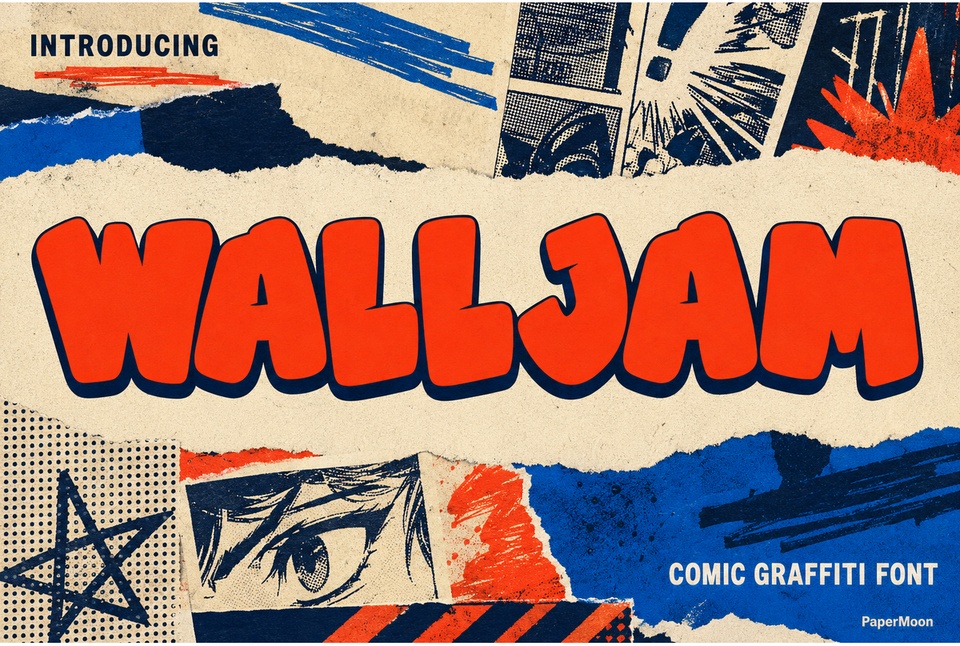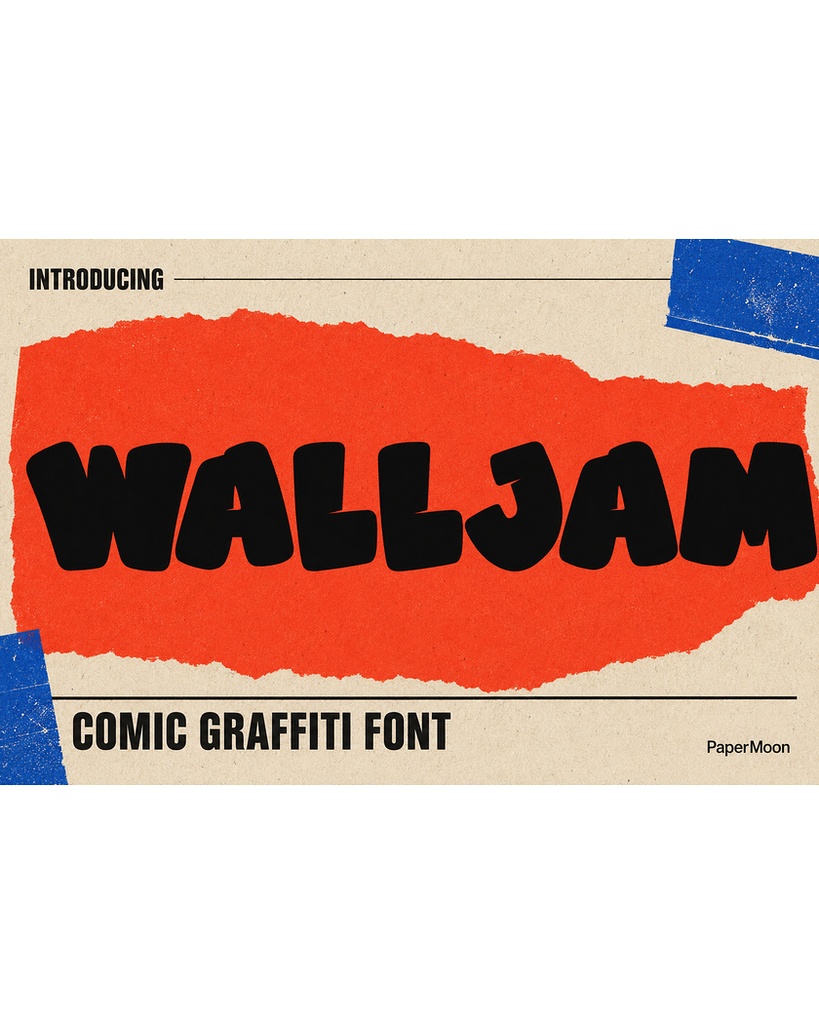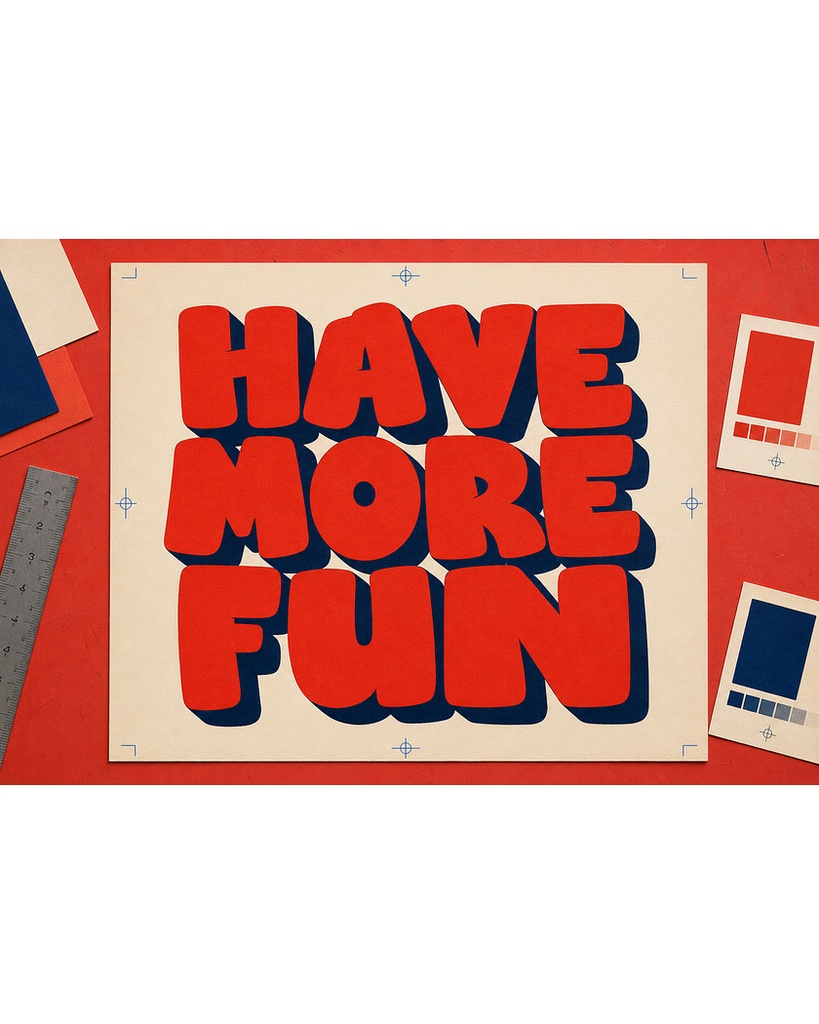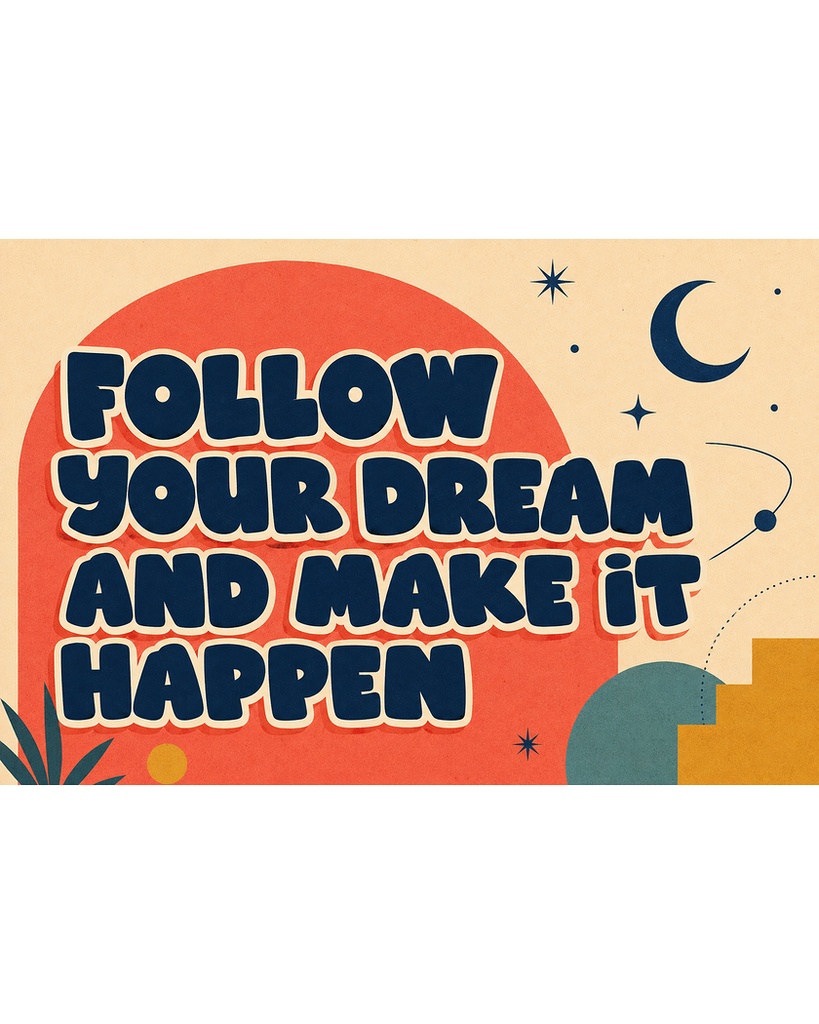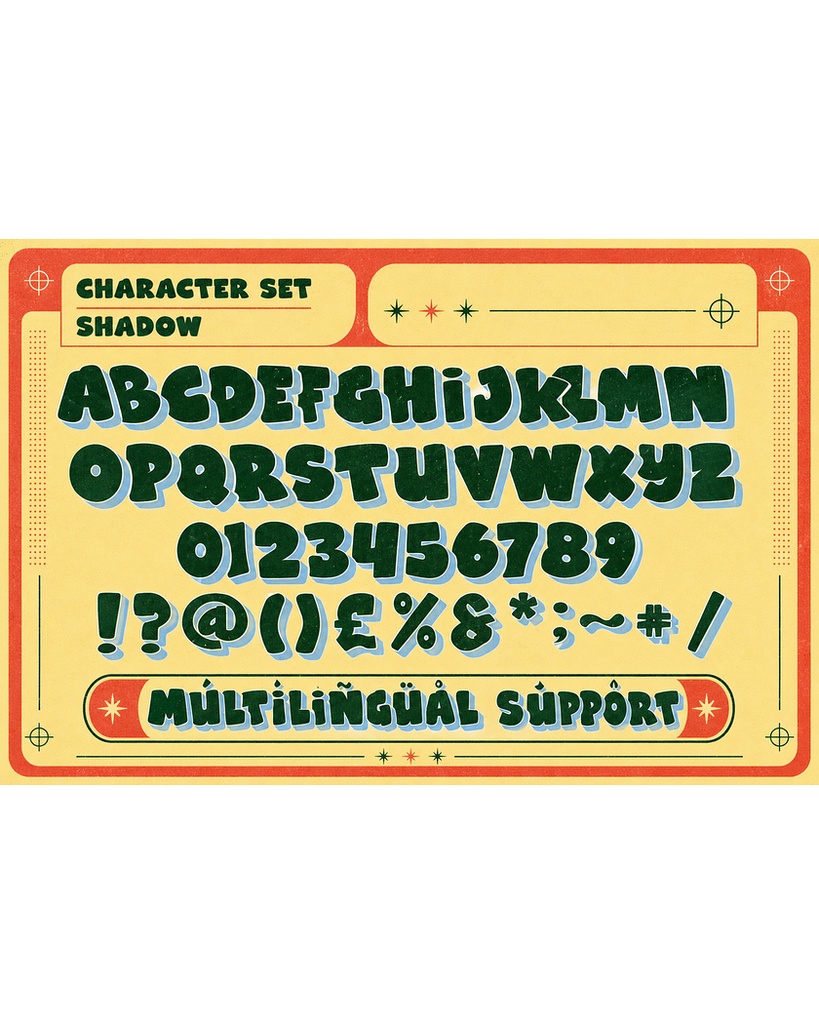
WallJam - 3Dシャドウ内蔵のコミック風グラフィティディスプレイフォントデュオ
**WallJam**は、目を引く手描き文字を求めるデザイナーのために作られた、コミック×グラフィティスタイルのディスプレイフォントデュオです。太く存在感のある大文字、弾むようなリズム、マーカーで描いたようなエネルギーが、見出しに本格的なストリートアートフォントの雰囲気を与えます。一方で、遊び心のあるコミックブックらしいテイストが、攻撃的になりすぎず親しみやすい印象を演出します。ストリートアート系のディスプレイフォントとして、WallJamはポスターやバナーなどの大きなサイズで特にその魅力を発揮し、不規則な手描きペイントの質感を存分に楽しめます。 ### WallJamとは WallJamは、異なる2つのスタイルを組み合わせて使える、本格的なフォントデュオです。**WallJam Regular**は、力強い字形と不規則な手描きテクスチャを備えた、コミックブックスタイルのベースフォントです。機械的ではなく、手作業で描かれたような自然な雰囲気を見出しに与えます。 **WallJam Shadow**は、Regularと同じレタリングに立体的な3Dドロップシャドウを組み込んだスタイルです。この3Dシャドウフォントを使えば、追加のエフェクトレイヤーを作成することなく、1回の設定で文字に奥行きを加えられます。 ShadowスタイルをRegularの上に重ねれば、本格的な立体感のあるポスターデザインを作成できます。また、Shadowだけを使用すれば、複雑な設定なしでポップな立体感を表現できます。すべてのアウトラインは手作業で描かれ、統一感のある本格的なアーバングラフィティフォントの雰囲気になるよう丁寧に調整されています。 ### 主な特徴 各スタイルには**236種類のグリフ**が収録されており、Basic Latin、Latin-1 Supplement、西ヨーロッパ言語の句読点に対応しています。さらに、一般的な数学記号、通貨記号、numero記号、商標記号なども含まれています。 OpenTypeのGSUB機能による標準的な**fi / fl リガチャ**を搭載し、GPOSカーニングによって、どのサイズでも文字間隔をバランスよく保てます。 インストール可能な埋め込み形式を採用しているため、MacとPCの両方にスムーズにインストールできます。 WallJamは、細部まで手描きにこだわったフォントです。このような手描きディスプレイフォントは、大型ポスターから小さなラベルまで、どのサイズでも個性的な表情を保ちます。また、太く存在感のあるレタリングでありながら、限られたスペースでも読みやすさを維持します。 ### 使用用途 コミックグラフィティフォントや遊び心のあるディスプレイフォントとして、WallJamは幅広いデザインプロジェクトに活用できます。 イベントフライヤーやアルバムアートでは、インパクトのある**ポスターフォント**として活躍します。ダイカットステッカーやバッジには、個性的な**ステッカーフォント**として使用できます。 ストリートウェアのデザインでは、アパレルやグッズに瞬時に個性を与え、小規模ブランドのブランディングにも適した**ストリートウェアフォント**です。 また、パーティー招待状や学校・教室での制作物などには、親しみやすい**キッズフォント**としても使用できます。 コミックブックのレタリングをベースとしたデザインなので、コミック、ZINE、個人経営の小規模ビジネスの遊び心あるブランディングにもぴったりです。 ゲーム開発では、HUDタイトルやメニュー用の**ゲームフォント**や**ゲーミングHUDフォント**として活用できます。コンテンツクリエイターにとっては、視認性が高くインパクトのある動画向けの**YouTubeサムネイルフォント**としても便利です。 内蔵されたShadowスタイルによって、追加作業なしで奥行きのある文字を作れるため、YouTubeサムネイルなどの目を引くデザインにも適しています。 さらに、**ブランディングフォント**や**ロゴフォント**として使用すれば、ブランド名やワードマークに自信のある手描きの個性を与えられます。その遊び心のあるスタイルは、パッケージ、商品ラベル、SNS用グラフィックなどにも自然に馴染み、カートゥーンらしいエネルギーと太く存在感のある文字表現を提供します。 ### 対応環境・収録形式 各スタイルは以下の4形式で提供され、合計**8種類のフォントファイル**が収録されています。 * OTF * TTF * WOFF * WOFF2 OTFとTTFはMacおよびPCにインストールでき、以下のデザインソフトで使用できます。 * Adobe Illustrator * Adobe Photoshop * CorelDRAW * Procreate WOFFおよびWOFF2は、`font-face`を使用したWebフォントとして利用できます。 フォントファイルをOSにインストールした後、使用するデザインアプリケーションを再起動し、フォントメニューから**WallJam**または**WallJam Shadow**を選択してください。 ### ライセンス クライアントワーク、ブランディング、商品制作、広告キャンペーン、その他の有料プロジェクトで使用する場合は、**Cubebrush Commercial License**を選択してください。使用可能な範囲については、現在のCubebrushライセンス規約をご確認ください。 **Basic License**は、個人利用および非商用プロジェクトのみに使用してください。 フォントファイルそのものの再配布・再販売は許可されていません。 ### WallJamでデザインに個性を 次の遊び心あふれるプロジェクトに、太く大胆で手描き感のあるスタイルを加えてみませんか? **WallJam**なら、コミックの楽しさ、ストリートアートのエネルギー、手描きレタリングの個性をひとつのフォントデュオで表現できます。